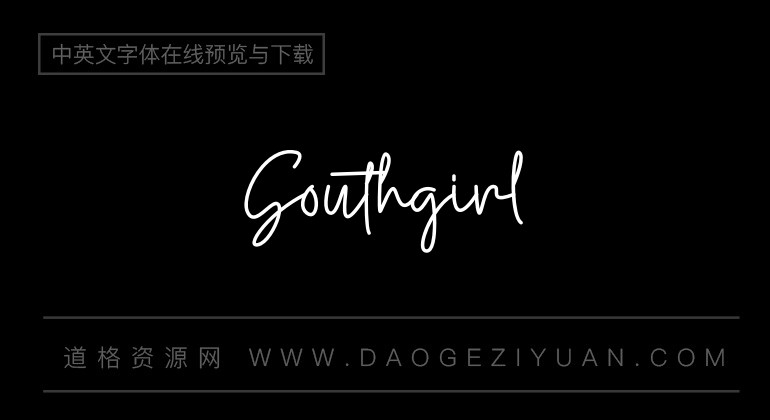
? Southgirl 字体是一款温柔、可爱、漂亮的手写字体,适合用于制作海报、卡片、标签等,它的外观轻柔可爱,让人一看就喜欢。它有着自然的手写感,让你的文字更加活泼有趣,给人一种温暖的感觉。内容介绍
Southgirl是一款非常不错的手写艺术字体,具有很好的视觉感,适合于文化类的宣传设计、商业类品牌的广告和产品包装设计以及个性化文字排版等较多场景。